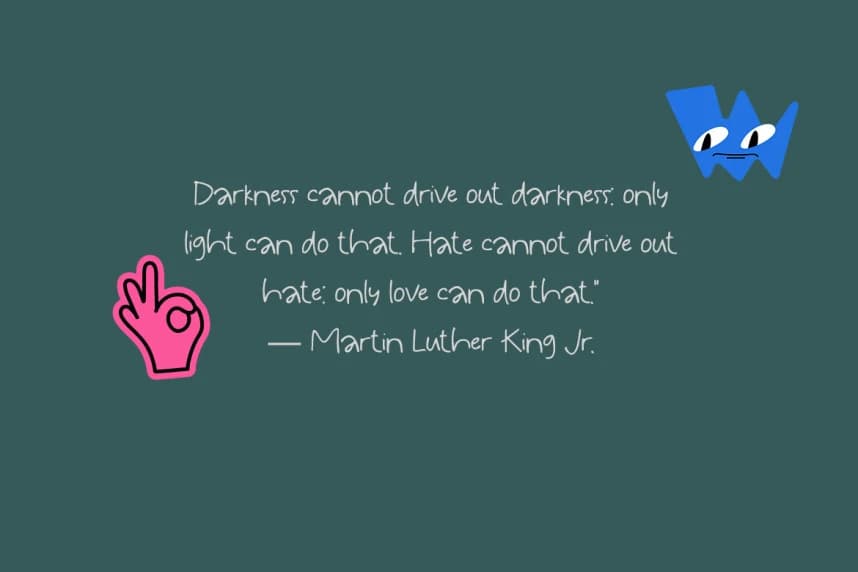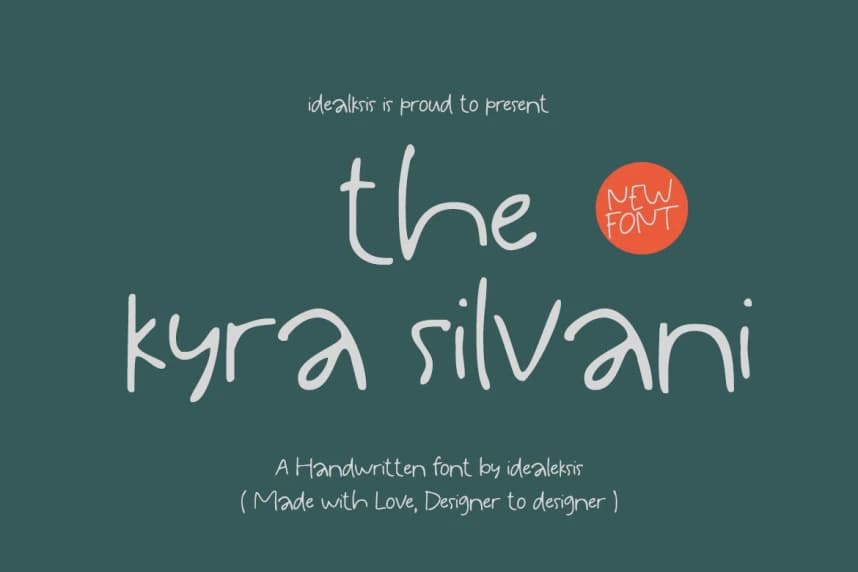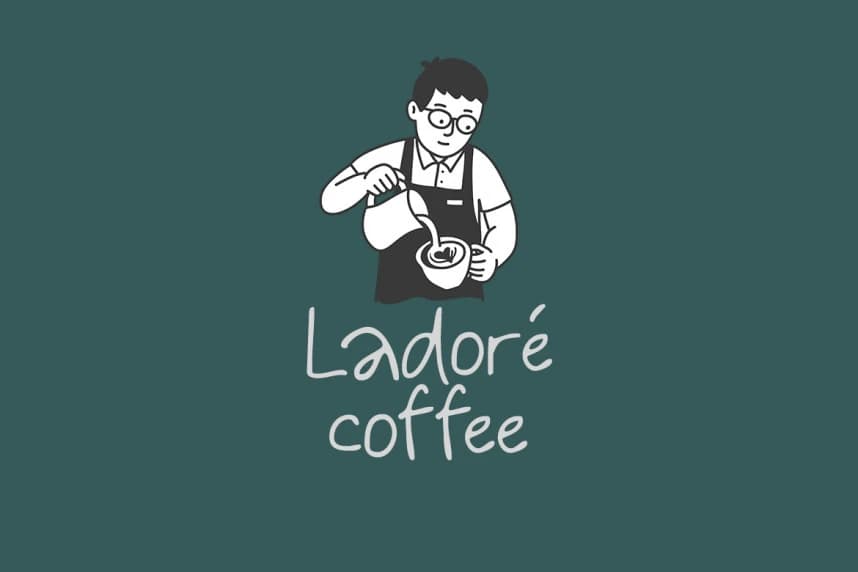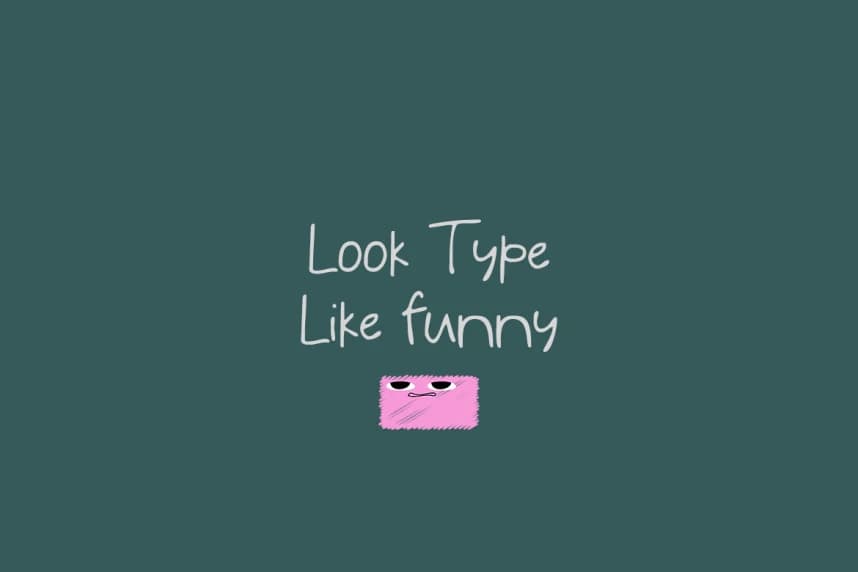
The Kyra Silvani Font, kişisel bir dokunuşla ve tasarımcılardan tasarımcılara hitap eden bir yaklaşım taşıyan oyunbaz bir el yazısı tipografisidir. Onun rahat çizgileri ve organik akışı ona sıcak, ulaşılabilir bir kişilik kazandırır; özgünlük ve yaratıcılığı çağrıştırır.
The Kyra Silvani Font, kişisel, tasarımcıdan tasarımcıya dokunuşla tasarlanmış oyuncu bir el yazısı tipografisidir. Sade hatları ve organik akışı ona sıcak, yaklaşılabilir bir kişilik kazandırır; özgünlük ve yaratıcılığı çağrıştırır.